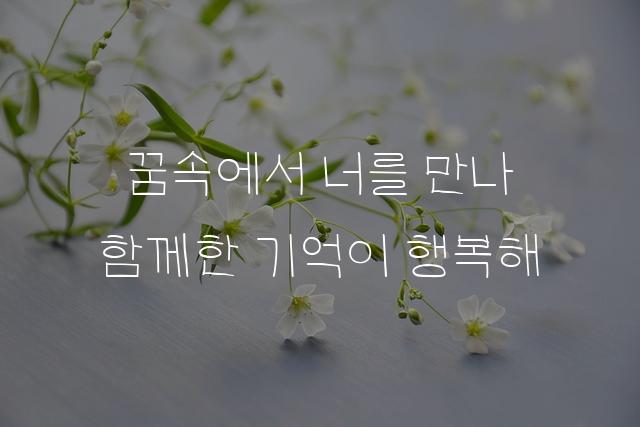
천안꿈누리터 꿈체
천안꿈누리터 꿈체는 펜으로 정성스레 쓴 듯한 귀여우면서도 또박또박한 글씨체를 제공합니다. 어린이의 순수함과 즐거움을 담아 따뜻한 감성을 전달하고자 만들어졌습니다.
이 폰트의 인사이트!
따뜻하고 친근한, 마치 아이가 이야기하는 듯한 목소리
천안꿈누리터 꿈체은(는) 귀여운 스타일, 펜/붓터치 계열의 생김새를 가지고 있으며
어린이 책, 일기/편지 등에서 자주 활용되며, 효과적인 메시지 전달에 적합합니다.
이 폰트는 교육, 유아/가족 분야에 잘 어울리며,
친근한, 편안한 느낌을 담고 있는 것이 특징입니다.
이 폰트와 유사한 폰트로는 나눔손글씨 교육, 바른펜체, 소망체 등이 있어요. 함께 비교해 보시면 좋습니다!